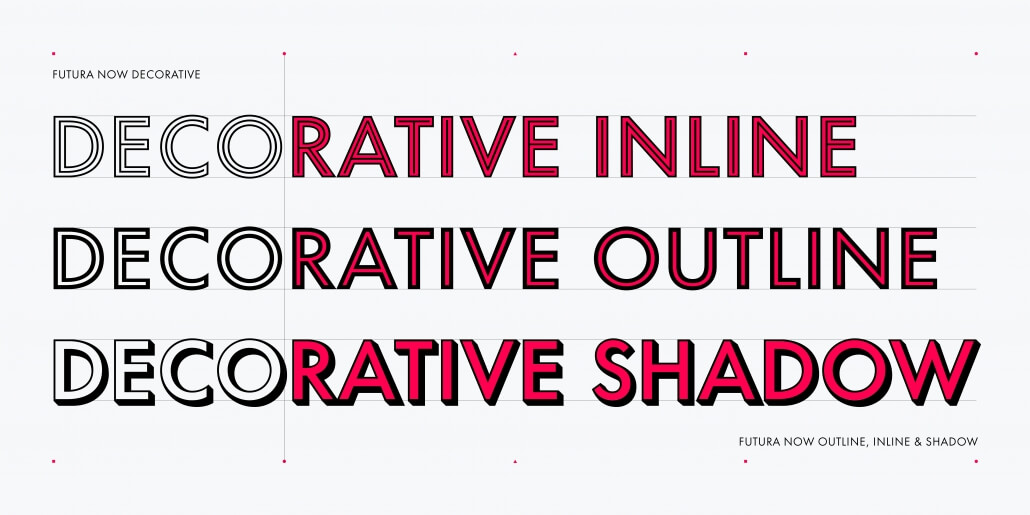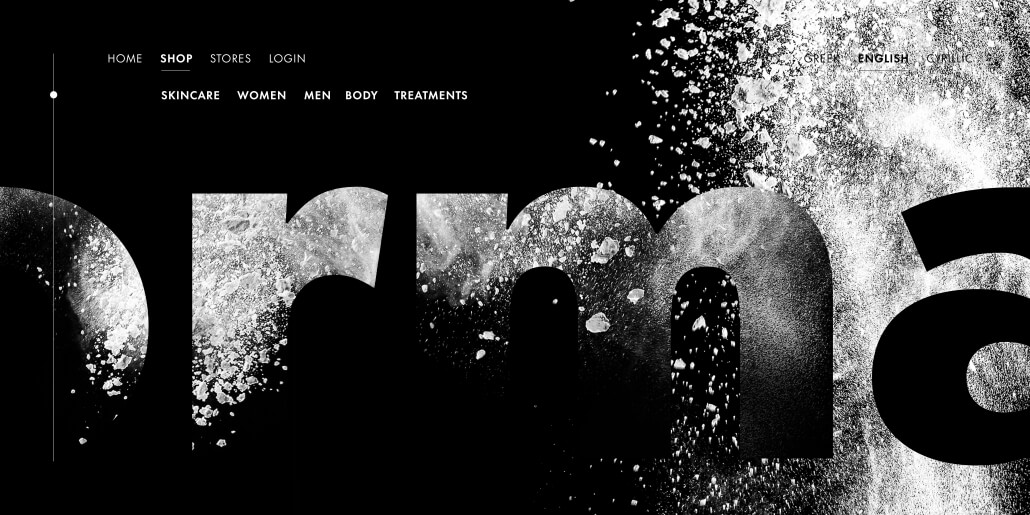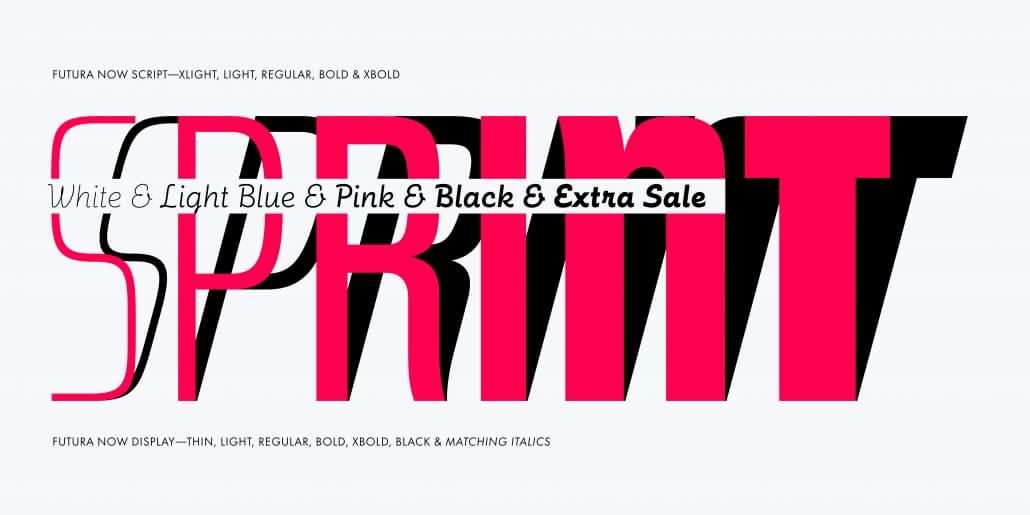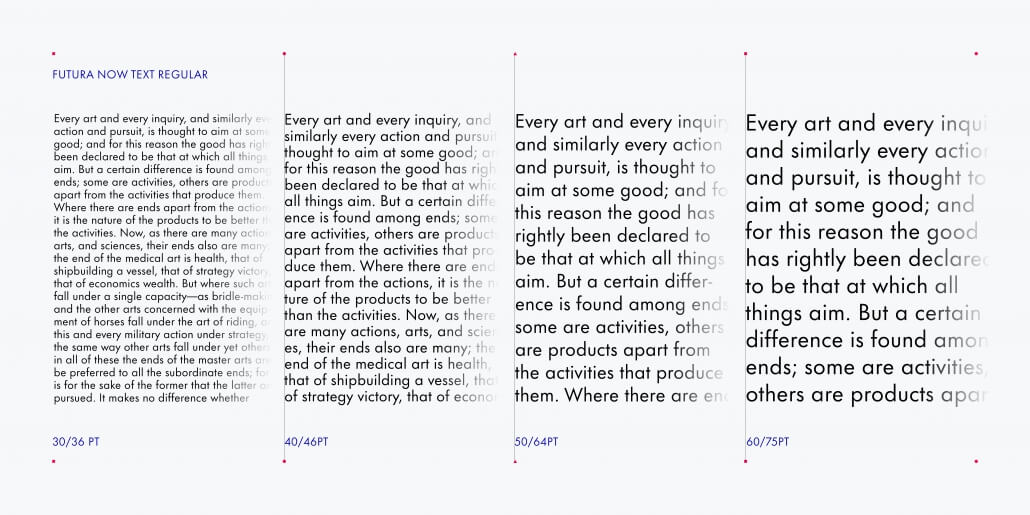
Futura Now: Die moderne Version eines Klassikers
Monotype hat die einst von Paul Renner entworfene Schriftfamilie »Futura« weiterentwickelt. Mit »Futura Now« möchte man den Klassiker fit für das digitale Zeitalter machen und präsentiert über 100 Schnitte.
Seit ihrer Einführung durch Paul Renner vor über 90 Jahren, zur Blütezeit der Bauhaus-Bewegung, haben zehntausende Marken, Verlage und Agenturen die Futura-Familie* genutzt. Im Laufe der Jahrzehnte hat sich die Schriftfamilie stetig weiterentwickelt und fand in zahlreichen Branchen Verwendung.
»Sogar auf dem Mond kam sie zum Einsatz, wo NASA-Astronauten sie 1969 auf einer Gedenkplakette zurückließen«, berichtet Monotype. »Gleichwohl waren die letzten Futura-Veröffentlichungen für die Verwendung im digitalen Umfeld nur eingeschränkt brauchbar.«
Mit »Futura Now« legt das Unternehmen nun die, nach eigenen Angaben, »genaueste Interpretation von Renners ursprünglicher Idee« vor und erweitert sie gemäß der Philosophie ihres Schöpfers so, dass sie den Ansprüchen des Digital first-Zeitalters sowie denen zukunftsorientierter Marken und Verlage gerecht werden soll.
Der Futura die »moderne« Identität zurückgeben
Unter den insgesamt über 100 Fonts* findet man 37 komplett neu entwickelte Schnitte – zum Beispiel ergänzende Strichstärken im Headline- und Textbereich, Script- und Display-Designs, sowie dekorative Varianten wie »Kontur«, »Inline«, »Shadow« und einen speziellen Font für Halbton-Ebenen-Effekte.
Ein Satz leichterer Schnitte soll Designern dabei helfen, auch klein gesetzte Texte für Print und Bildschirm optimal lesbar zu gestalten. Als komfortabel sollen sich dabei die neuen Text- und Headline-Unterfamilien erweisen.